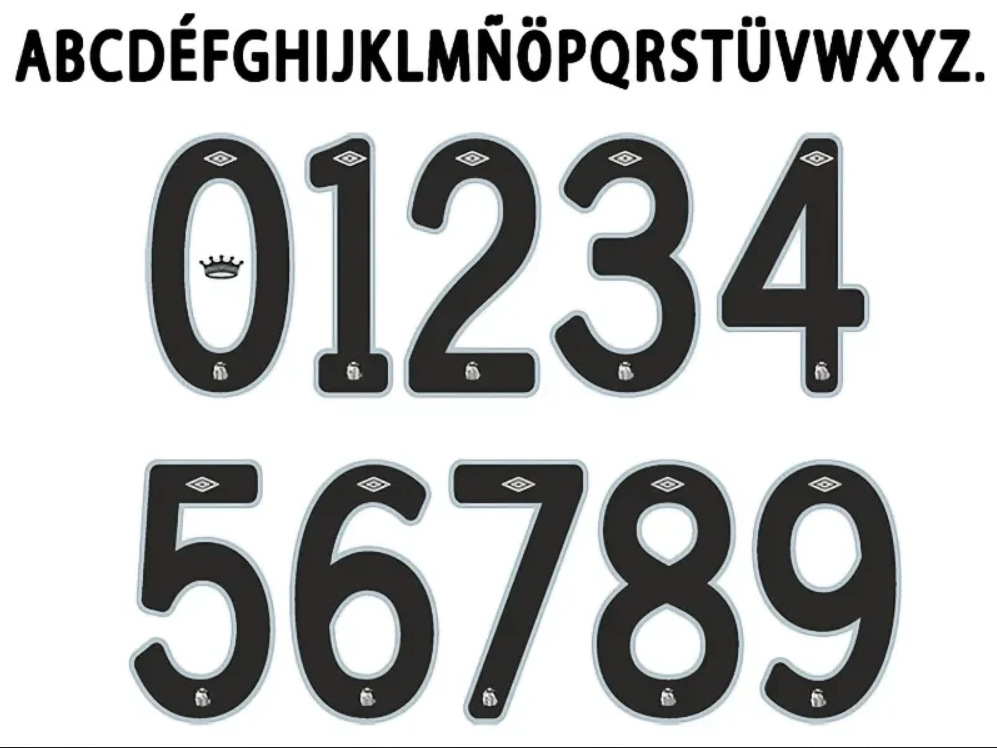
A temporada 2025 chega com novas expectativas para o Alvinegro Praiano. E para quem trabalha com personalização de camisas ou criação de conteúdo digital, ter acesso aos detalhes oficiais do uniforme é fundamental.
Neste post, trazemos o arquivo completo da tipografia utilizada pela Umbro nos uniformes do Santos FC para a temporada 2025. Ideal para estampar o manto sagrado da Vila Belmiro com a máxima fidelidade.
- Conteúdo: Alfabeto completo (caixa alta) e numeração oficial com o logo da marca na base.
Estilo Visual e Identidade
A parceria histórica entre o Santos e a Umbro costuma entregar fontes que respeitam a tradição do clube, mas sempre com um toque de modernidade.
Para 2025, a tipografia aposta em uma estética limpa e geométrica, garantindo alta legibilidade tanto na clássica camisa branca quanto no uniforme listrado. Os números possuem espessura média, com cortes estratégicos que remetem à velocidade e ao dinamismo dos Meninos da Vila. É uma fonte versátil, que transmite seriedade e peso histórico, perfeita para reproduzir nomes de ídolos ou criar camisas personalizadas para torcidas organizadas.